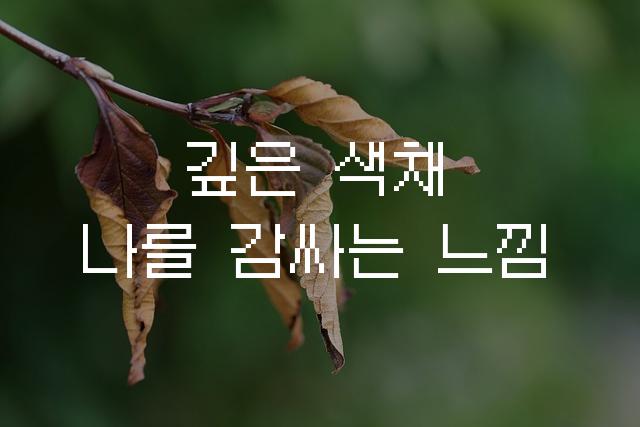
갈무리11은 레트로와 픽셀 도트 감성이 결합된 독특한 폰트입니다. 과거의 게임기 그래픽을 연상시키는 디자인으로, 디지털과 아날로그의 경계에서 감성을 자극합니다.
갈무리11은(는)
픽셀/코딩, 레트로, 감성적인, 복고풍, 게임 느낌 계열의 생김새를 가지고 있으며
포스터, 초대장, 일기/편지 등에서 자주 활용되며, 효과적인 메시지 전달에 적합합니다.
이 폰트는 크리에이티브, 문화/예술, 이벤트/웨딩 분야에 잘 어울리며,
감성적인, 창의적인, 예술적인 느낌을 담고 있는 것이 특징입니다.